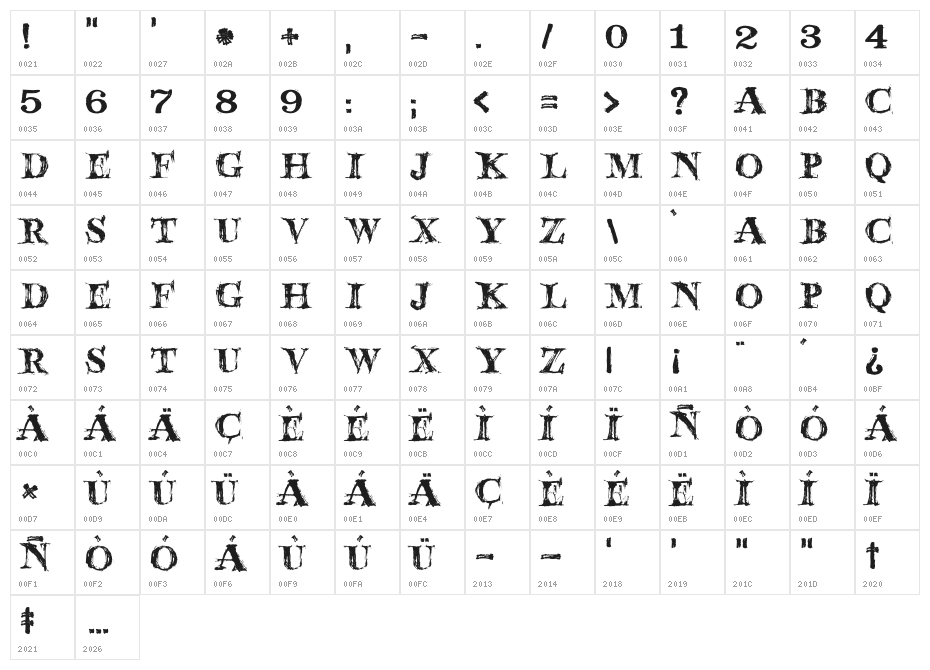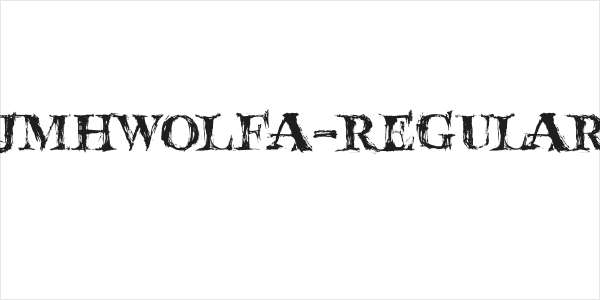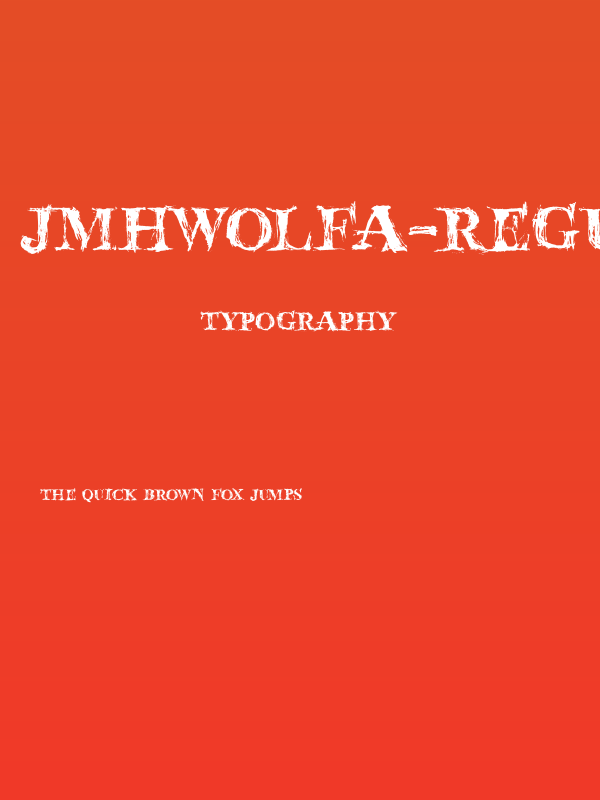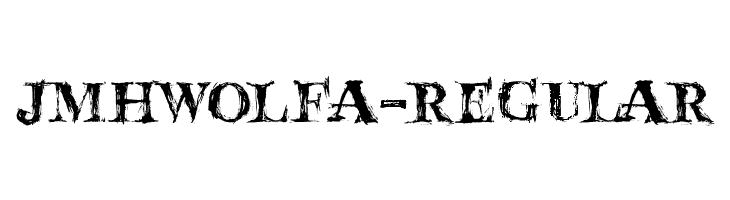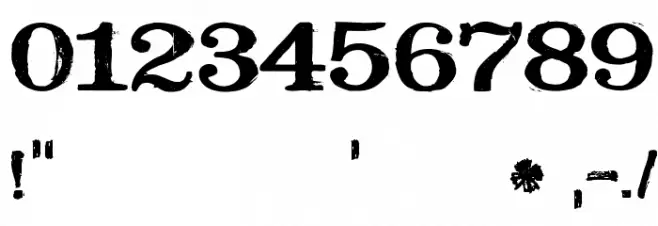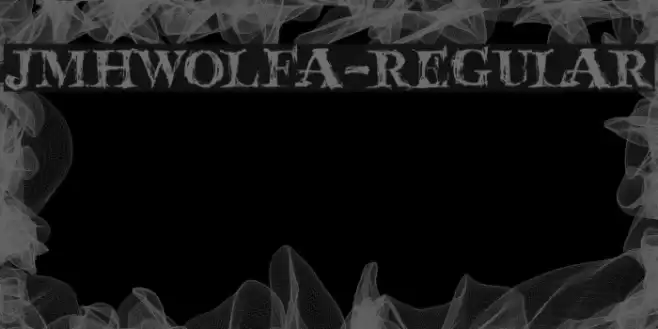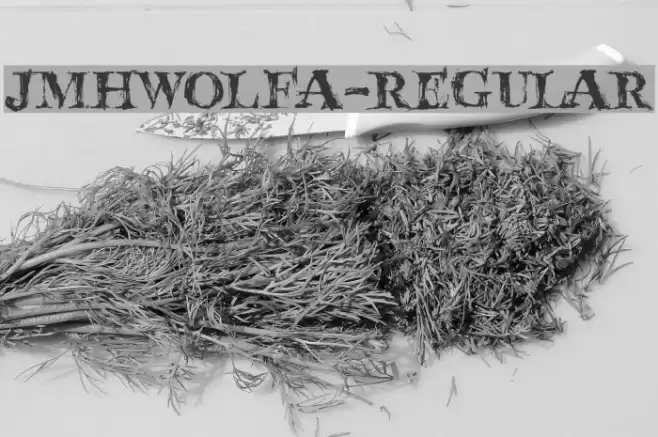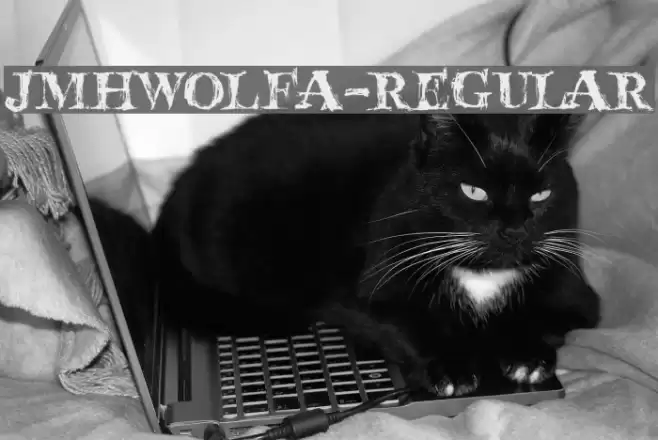
JMHWolfa-Regular Font
| Estilo general | Vintage, Grunge |
| Proyectos propuestos | Ideal for posters, album covers, branding for edgy or alternative products, and any design needing a vintage or grunge aesthetic. |